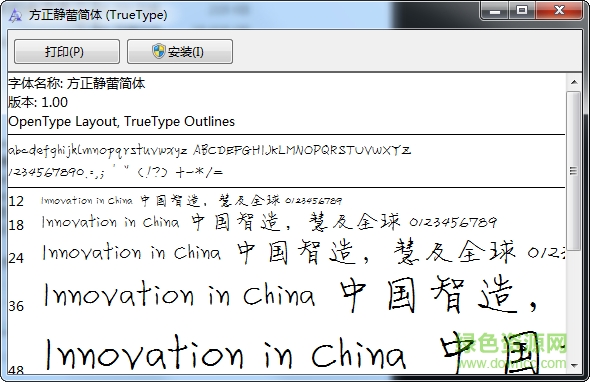
方正電子攜手徐靜蕾發(fā)布了其個(gè)人書法計(jì)算機(jī)字庫(kù)產(chǎn)品,這款被命名為“方正靜蕾簡(jiǎn)體”被方正方面稱為我國(guó)第一款真正意義上的個(gè)人書法計(jì)算機(jī)字庫(kù)產(chǎn)品,宣稱標(biāo)志著“計(jì)算機(jī)字庫(kù)”將進(jìn)入個(gè)性化時(shí)代。按照GB2312國(guó)家標(biāo)準(zhǔn),6763個(gè)漢字,682個(gè)標(biāo)點(diǎn)符號(hào),94個(gè)包括英文字母和數(shù)字在內(nèi)的ASCII字符,書寫在有100多個(gè)1.2厘米見方格子的A4紙上。字體骨骼清秀、遒勁有力,清冽而又優(yōu)雅、從容,令人賞心悅目。字如其人,心素如簡(jiǎn),人淡如菊。特別適用于書寫信函、報(bào)告、文章等。